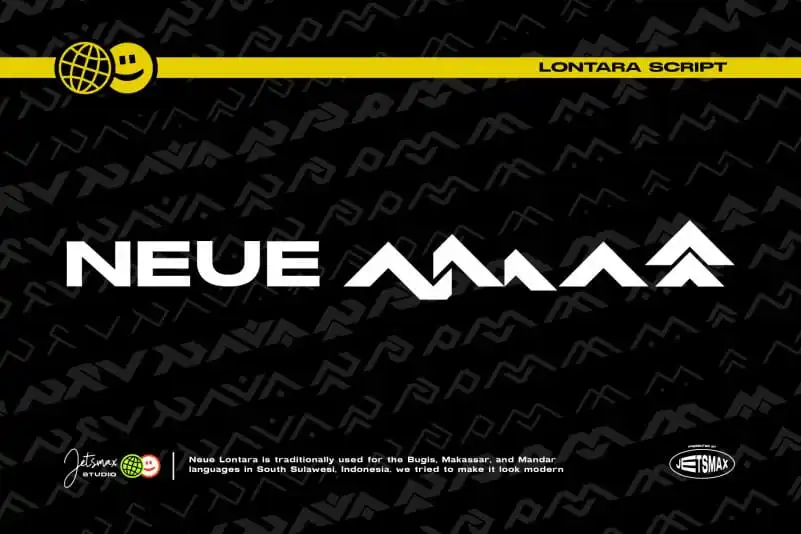
Neue Lontara Display Font – Download Grátis
A Neue Lontara Display Font é uma fonte de script tradicional indonésio que oferece uma visão única dos idiomas regionais mais ricos do país. Uma das línguas regionais que merecem destaque é o makassar, uma das 739 línguas de Indonesia. A Neue Lontara Display Font celebra essa diversidade cultural, especialmente para a comunidade Makassar e suas centenas de outras linguagens regionais. O uso desta fonte não apenas dá vida aos textos tradicionais do makassar mas também salienta seu valor único em meio à riqueza linguística da Indonesia. A fonte é um tributo à cultura, ao conhecimento local e às histórias que se codificaram nas letras desde tempos imemoriais. Engenhosa e sofisticada, ela permite a criação de textos que destacam tanto o significado quanto a beleza visual dos idiomas indonésios, especialmente do Makassar.